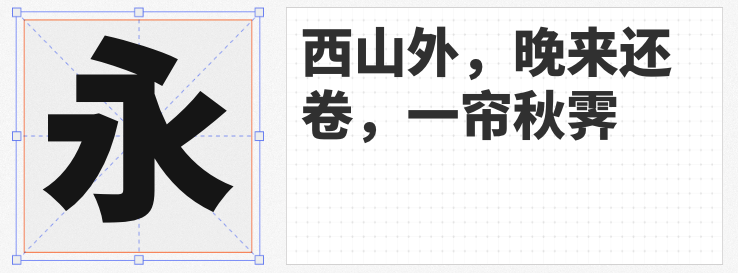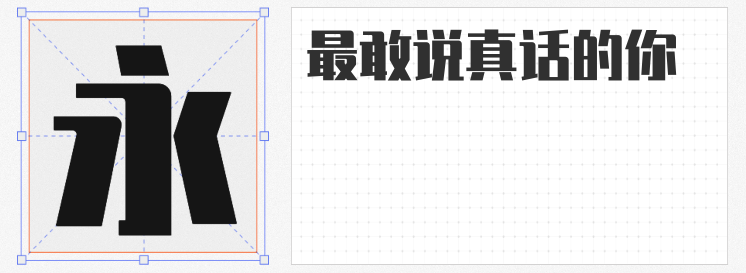
在平面设计中,超粗黑体以其强烈的视觉冲击力和独特的性格语言,成为标题设计、品牌标识和视觉海报的核心元素。本文精选四款免费可商用的超粗黑体,从笔触特征到应用场景,解析其如何通过字形设计传递力量感与现代美学。
作为锐字潮牌字库的代表作,锐字潮牌真言简2.0超粗以「直角与圆角的错落搭配」打破传统黑体的刻板印象。其笔触浑厚如刀刻,横画收笔处微妙的圆角处理,让字体在刚硬中透出柔和,适合科技、运动类品牌的视觉表达。
作为Adobe与Google联合开发的开源字体,思源黑体SC Heavy以七级字重体系构建了完整的视觉层次。其超粗版本笔画宽度达普通字体的3倍,中宫紧凑而字面开阔,在保持可读性的同时强化视觉张力。
华为定制的这款字体,在超粗字重中融入书法美学:短笔画保持横平竖直的理性结构,长笔画则通过微妙的弧度变化传递书写韵律。其「撇捺弯钩」的笔势处理,让字体在极粗状态下仍保持灵动,非常适合智能硬件、新能源汽车等前沿科技领域的品牌视觉系统。
基于思源黑体等六款开源字体改造的句读黑体,其超粗版本以「开放字怀」设计提升小字号下的识别度,同时支持简体中文、繁体中文、日文、韩文及拉丁字母的无缝混排。字体采用SIL Open Font License 1.1授权,企业可自由用于商业项目而无需支付版权费用,是跨境电商、多语言出版物的理想选择。
这四款超粗黑体,既有开源字体的技术普惠性,又通过独特的字形设计满足差异化需求。无论是追求几何美学的科技品牌,还是需要多语言支持的全球化企业,都能在这些字体中找到力量与美学的平衡点。